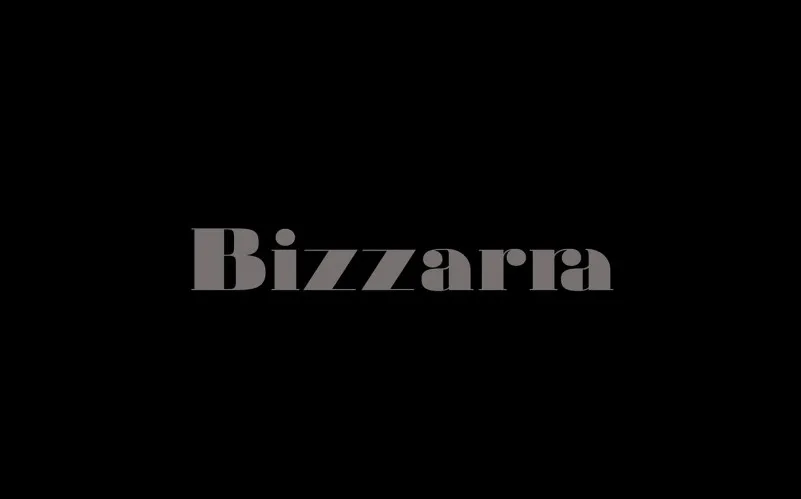
A Bizzarra Serif Font é uma nova opção para designers que buscam uma tipografia serif moderna com inspiração clássica. Criada por Wal Glezar, esta fonte luxuosa traz contrastes notáveis entre os ramos finos e as serifs ultra-leves. Isso resulta em um desenho único e chamativo. A Bizzarra vem equipada com 235 caracteres, incluindo letras maiúsculas e minúsculas, números old-style, símbolos e ligaturas de conjuntos de letras. Para os designers que procuram uma fonte sofisticada para projetos digitais ou impressos, esta seria uma ótima escolha. Com sua combinação única de formas finas e serifs leves, a Bizzarra Serif Font oferece aos criadores um desafio visual interessante e atemporal.